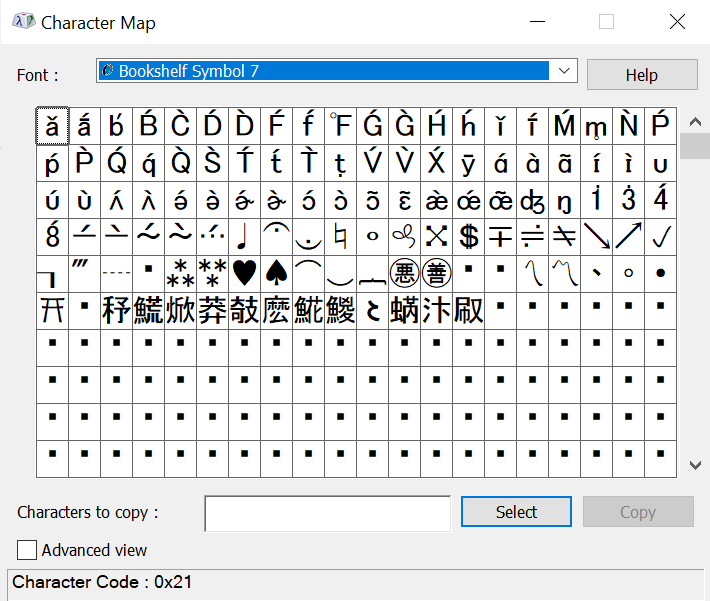
0 $danielandrian00221$ Posted November 10, 2024 2 hours ago, stefanusdany said: Ada yang tau atau punya rekomendasi? thank you all Kamu bisa membuka pencarian pada windows kamu atau WIN + S. Ketikkan Character Map. Cari Font yang bernama Bookshelf Symbol 7. Note: Pada font tersebut hanya beberapa huruf kanji saja yang work untuk modif di JG:RP.
0 $G H O S T$ Posted November 10, 2024 Cari font nya pakai character map, font nya sudah ada bawaan dari windows, jadi gak khawatir kalo kita bikin stiker pasti bakal keliatan juga di orang lain (kecuali sudah install atau pakai font yang bukan bawaan windows). Untuk tutor nya bisa ngikutin dibawah ini : Dan biasanya untuk font jepang gua biasa make Bookshelf Symbol 7.